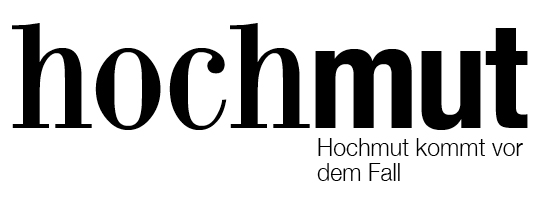
Schriftmischung BodoniXT und Neue Helvetica
Ich würde mich über Rückmeldungen zur Schriftmischung von BodoniXT und Helvetica Neue (hier Condensed Bold) freuen – und zwar ganz konkret in in dieser Art und Weise:
Außerdem sind Rückmeldungen/Ideen/Anregungen etc. ganz herzlichen wilkommen
• zur Komplettidee (es soll schon was Logo-mäßiges für versch. Publikationen werden)
• zu (möglichst freien) Alternativen für beide Schriften (BodiniXT habe etwa nur diesem einen Schnitt), die sich in ähnlicher Weise für eine solche Sache eignen
• sowie zu folgendem Thema: Innerhalb der Publikationen sollen möglichst die verwendeten Logo-Schriften wieder aufgegriffen werden. Welche Serifenschrift könnte man für den Fließtext einsetzen, wenn diese beiden anderen ggf. bleiben?
Ich finde die Schriftmischung abgesehen von der Zusatzzeile in Ordnung. Die beiden Schriften passen in dieser Anwendung wirklich gut zusammen. Die Subline (Bibelzitat) klemmt für meine Begriffe aber zu sehr an der Wortmarke und wirkt sehr klein. Die Frage ist, ob man »Hochmut« da überhaupt noch mal schreiben muss?
Worum geht es denn konkret? Was soll kommuniziert werden, wen will man erreichen, wer ist der Absender, etc. :-?
Zunächst einmal freut es mich, dass die Mischung der Hauptzeile scheinbar so passt.
Wie in meinem letzten Fragen-Beitrag geht es – sorry, hatte ich direkt erwähnen können – um eine Logo-Idee für eine nachwuchswissenschaftliche Zeitschrift (Kultur-, Kunst-, Medienwissenschaften). Da der genaue Titel noch nicht steht, war das mit dem Hochmut nur ein Test.
Die Unterzeile (Neue Helvetica Light) gefällt mir auch noch nicht. Da so etwas aber ganz bestimmt benötigt wird und unter Umständen länger sein kann, hab ich sie mal zweizeilig dran gepackt.
Und es besteht das Problem, dass im Heft für die Texte eigentlich eine Serifen-Schrift verwendet werden soll, weshalb sich mir momentan die Frage stellt, wie ich die Logo-Schriften innen wieder aufgreifen kann oder ich davon besser komplett absehe…
Bodoni scheint mir da insgesamt nicht so geeignet, oder?
Für Fließtexte ist die Bodoni eher weniger zu empfehlen, für Headlines jedoch schon. Auch die Helvetica würde ich persönlich im Mengensatz meiden.
Wenn Du das typografische Klima also gern so konsistent wie möglich halten möchtest, sollte man das Pferd vielleicht von der anderen Seite aufzäumen. Sprich: erstmal nach einer vorstellbaren Mengentext-Kombi (Serif/Sans) suchen und dann die Wortmarke daraus bilden. Wäre das denn vom Budget her denkbar? Ist gibt zum Beispiel einige Sippen, welche mit Display-Fonts ausgestattet wurden, aber auch eine mengentexttaugliche Version enthalten. Vielleicht mal in die Richtung denken?
Beipiele:
· Le Monde
· FF Absara
· FF Quadraat
· …
Trotzdem finde ich Deinen Mix sehr reizvoll und auch zum Thema passend. Sicher gibt es auch hier noch eine passende Schrift für den Mengensatz. Hast Du die Bodoni spaßenshalber mal getestet? Gibt es ein Layout-Beispiel?
Hier noch eine, die mehr klassizistisch angehaucht ist (also schon eher in Richtung Bodoni):
· Austin
Vielleicht auch noch interessant:
· Publico
Ähm … rollen wir das Thema Satzschrift gerade von Neuem aus? Welche Schlüsse hast Du denn aus dem letzten »Fragen-Beitrag« gezogen? Da ging es doch schon mal um eine Sans als Ergänzung zur Minion?! Beide hinfällig?
Nein, eigentlich nicht. Zur Auswahl stehen dort gerade Oswald, Myriad, Neue Helvetice, PT Sans, Chivo, News Gothic, Trade Gothic, Source Sans, die leider bisher noch nicht innerhalb unserer »Herausgeber-Gruppe« diskutiert wurden. Entscheidung also offen.
Das ist mir schon klar, ich habe mit den Beispielen nur die genannte Schriftklassen illustriert, weil ich denke dass man schneller ans Ziel kommt wenn man systematisch an der Sache rangeht. Welche Schriftkombination dann letztendlich am besten funktioniert kann ich auch nicht vorhersagen, dazu gibt es alleine was die Textschrift angeht zu viele mir unbekannte Variablen wie die Bandbreite der Inhalte, die Anzahl der gewünschte oder notwendige Hierarchiestufen in den Beiträgen, Vorlieben für Details, Kundenwünsche usw. die das Gesamtbild beeinflussen. Wenn wir bei der Logokombi bleiben wollen wäre es ebenfalls sinnvoll, wie vergleichbare Publikationen aussehen, ob es vielleicht Mitbewerber gibt die etwas ähnliches machen, genau die gleiche Schrift benutzen usw.